字体界的C位之争,40 款字体分享
不过今天要给你盘点不一样的,比如字体界的C位之争,见过吗?
木有,那就有请宇宙网红,字体界的杠把子——字由(此处掌声不要停),来一场公平公正,以数据说话的颁奖盛会。
咳咳~感谢大家的厚爱,这次主要分小组前十和最佳人气奖,我们先来看大屏幕:
有黑体、宋体传统字体,也有个性体、装饰体、书法体、手写体、卡通体,满足当下年轻人的口味。
接下来我就把话筒,移交给各组候选人,看你们的表现哦~
Hi,我是黑体,甲方爸爸的最爱,因为我看起来很man,很power,符合甲方“logo要大一点”的需求,所以经常被用于标题、标语、标志。
看看下面这些字体,你是不是经常用它们?
嗯没错,不过这里我要提醒一下,黑体≠粗体,它其实是西文中的“无衬线”,朴素、简洁、无装饰。看见阿丽达黑体 Light了吗,它就是细的代表,排名第三。
另一个是汉仪元隆黑-35简,占位第八。
看着很舒服吧!嗯,不过还是无缘冠军,因为谁都比不过看起来不粗也不细,又是免费商用,又是多语言支持的思源黑体 Medium,哈哈哈。
大家好,我是黑体的好基友,宋体,常用于书籍、杂志、报纸的正文排版,因为我很有历史的美感。
你看思源宋体又来占第一了,还带了四个家属(包括日文)。
不过,我也有新鲜的给你看~
比如华康雅宋体,笔画间加了一点圆角处理,更有亲和力,难怪排第二。
还有汉仪长美黑简,让小宇宙都能爆发了。
不过我最喜欢的,还是加了劲道的汉仪意宋(第三名),汉仪瑞意宋(第四名)。就差一个字,但一个是气质型,一个是高耸型,都用在了很多案例中。
最后我发现一个小秘密,变粗的宋体很受欢迎啊~
说完了传统字体,下面轮到个性体登场了,我们个个都深怀绝技~
首先就是2018火得不能再火的汉仪尚巍手书,之前还专门说过设计师,他是字体界的周杰伦,每100个人就有99人见过他的手写字……
这次共有三款尚巍家族字体占位前十,恭喜恭喜!
另外,比它更张扬的汉仪秦川飞影,更龙飞凤舞的汉仪孙万民草书,也分别是第三名和第五名。
不过也不是非要“视觉冲击”,才有个性,像汉仪颜楷(第二名)、汉仪新蒂唐朝体(第七名)、汉仪许静行楷(第九名),就怎么看都很耐看。
最让人惊喜的是汉仪游园体(第六名),看起来细细、圆圆的,却有复古的味道。
装饰体,提前给大家拜年了,我们的口号是,做活动要用我,做海报要用我……
不信你看,凭实力说话~
知道萌萌的雷佳音,用的是啥字体吗?就是排名第一的汉仪铸字童年体,连带着一家亲的汉仪铸字木头人,也登上了第三。
当然,常用的几款免费商用字也肯定在前十。
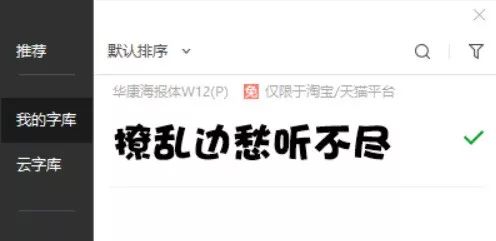
还有力量黑、锐智、雅酷黑、星球体,都炒鸡受欢迎~
看过来看过来,我是最有中国风,最有年味的字体,春联、福字、红包都交给我吧!
又要恭喜汉仪尚巍手书了,二次获奖,还是第一,羡慕嫉妒恨啊~
不过汉仪秦川飞影、汉仪尚巍流云体、汉仪孙万民草书、汉仪新蒂唐朝体、汉仪许静行楷,也都是双料夺主。
因《上新了故宫》大火的汉仪北魏写经,NO.5,实至名归,戳从邓伦的颜,到鲁班的萌,这部综艺凭啥让你欲罢不能?
还有汉仪雪君体、汉仪程行简,也都是大家最喜欢用的字体。
有人说,以前车马很远,书信很慢,一生只够爱一人,而我们手写体,就有这样的温度。
看过《原来你还在这里》吗?用的就是汉仪春然手书,字体尖锐有个性,冠军妥妥的了。
还有各种吸猫人群,都对汉仪喵魂体爱不释手,荣登季军的宝座。
说到猫,排名第七的濑户字体,也很卡哇伊,还免费商用哦~
汉仪新蒂系列,表现也很抢眼,连登三款。
最后,还漏了一个亚军选手,汉仪国强行书,居然还很适合春联。
为什么让我最后一个说,伦家是小孩纸,喜欢卡通的东东~
啊,汉仪铸字童年体又是第一,没意思~
华康海报体、汉仪铸字木头人、站酷快乐体、汉仪尚巍小时候、汉仪喵魂体、濑户字体,这些都看过了~
还有别的呢,这个汉仪黑荔枝体简怎么样,第五名哦。
还有这个汉仪趣黑,也很符合你的童心吧。
见过汉仪尚巍清茶体的表情包吗,哈哈哈~
好了,各组冠军选手已经产生了~
最后根据综合评分,全年及各月的使用量,我们选出了最佳人气前三名~